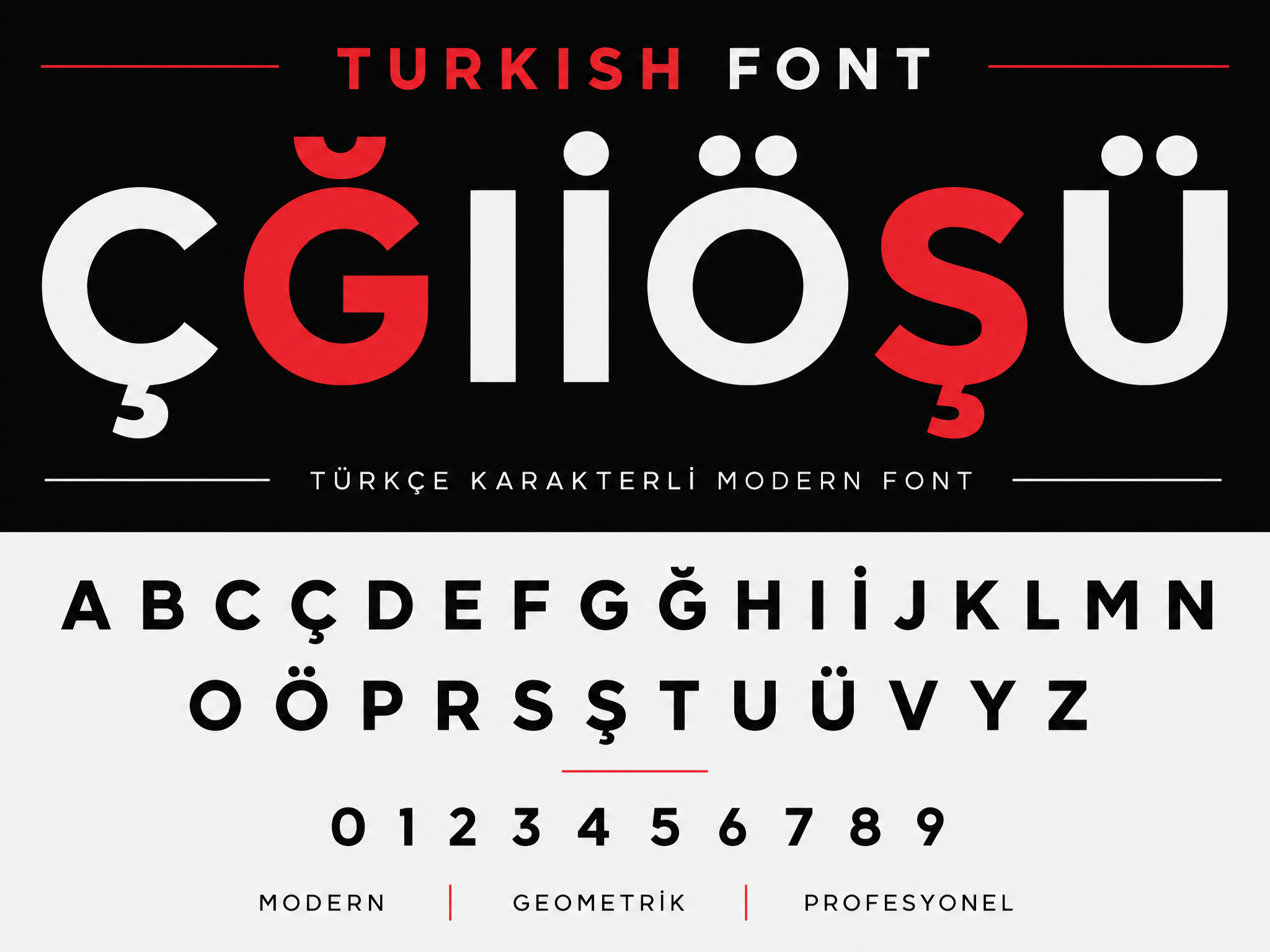
Türkçe Karakterli Modern Font; ç, ğ, ı, İ, ö, ş, ü dahil tüm Türkçe karakterleri kusursuz destekleyecek şekilde tasarlanmış çağdaş bir sans serif fonttur. Türkçe metinlerde sıkça yaşanan eksik veya bozuk karakter sorununu ortadan kaldırır. Geometrik ve temiz harf formlarıyla logo, afiş, sosyal medya ve web arayüzleri için idealdir. Yüksek kontrastlı yapısı büyük puntolarda güçlü, küçük puntolarda net bir görünüm sağlar. OTF ve TTF formatlarında teslim edilir; ticari kullanıma uygundur. Türkçe içerik üreten tüm tasarımcılar için güvenli bir seçimdir.
Türkçe Karakterli Modern Font